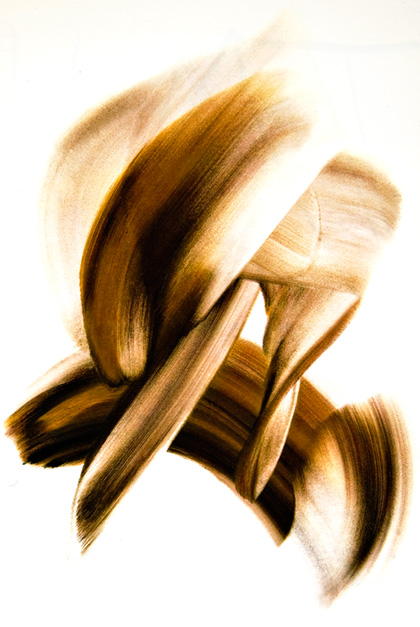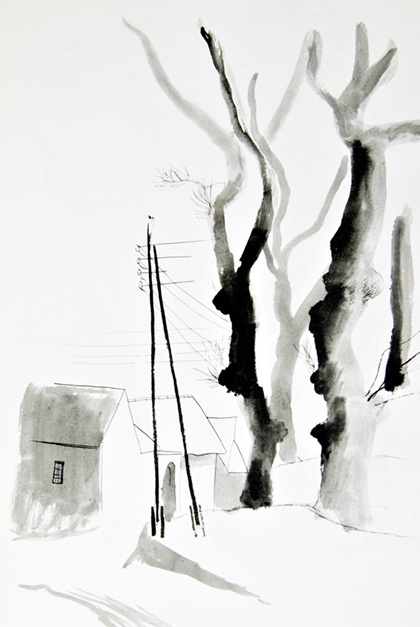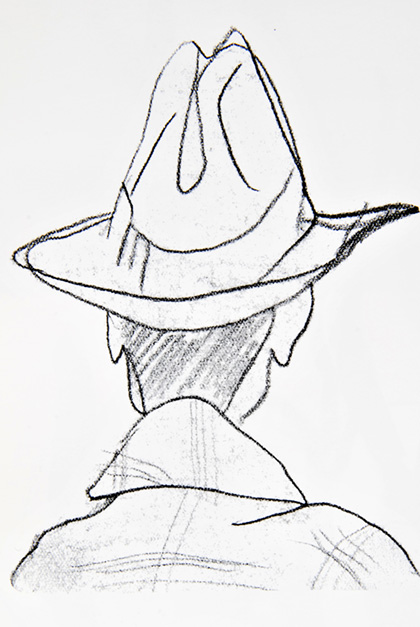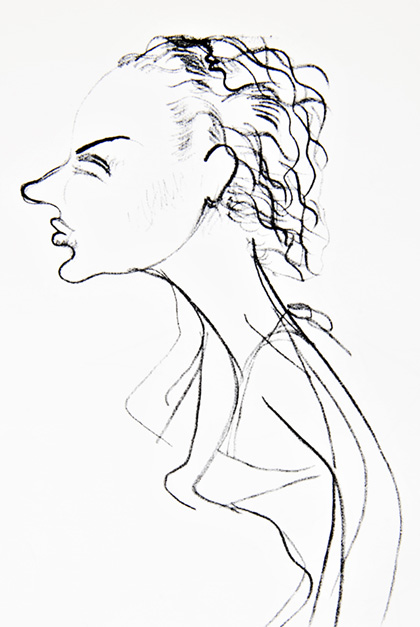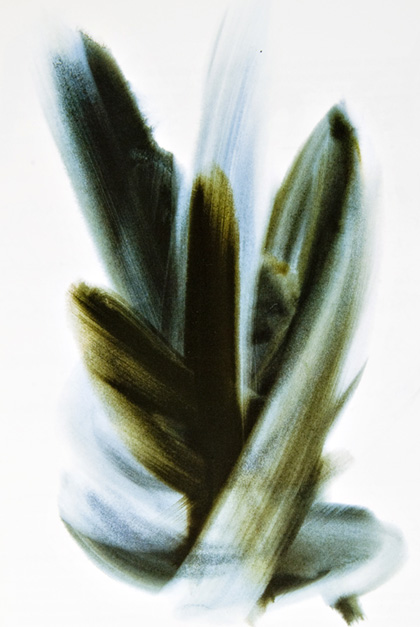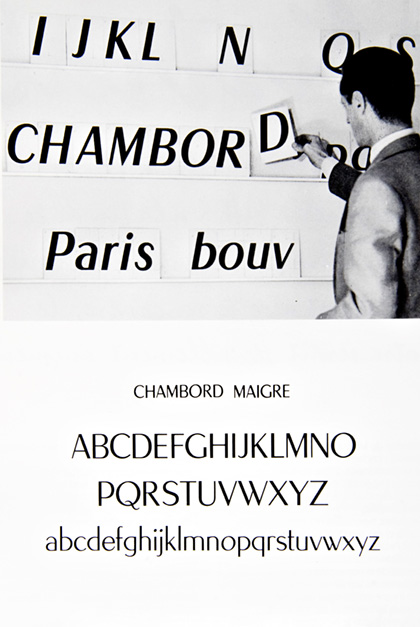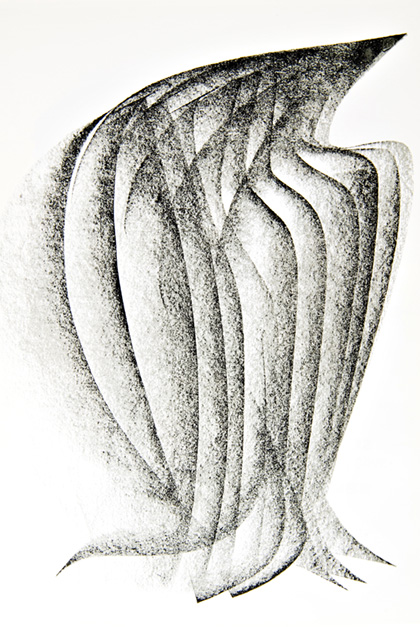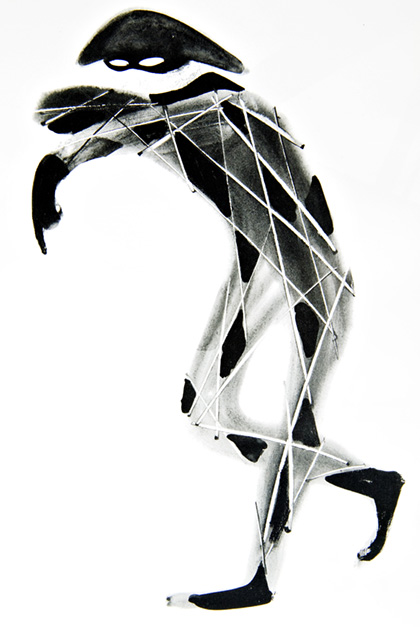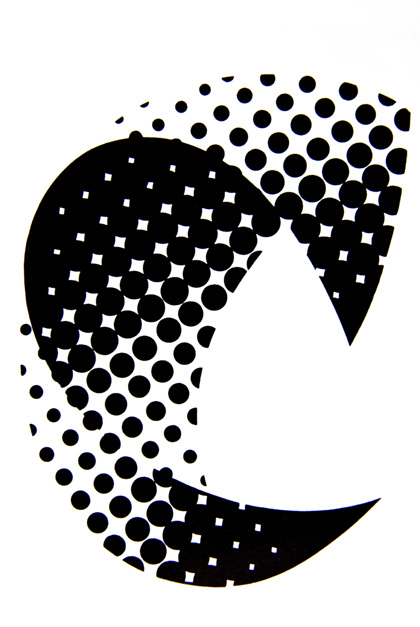
Roger Excoffon | Hommage au Graphiste et à l’homme | reloaded
À l’heure où j’entends que le nouveau logo d’Air France va parcourir la blogosphère à la vitesse du Concorde multiplié par 1000, je profite de republier ce billet sur Roger Excoffon qui fut le créateur inspiré du précédent logotype. Nous en reparlerons.
Ces images sont issues du catalogue de l’exposition qui se tint au Musée de la Monnaie peu après la disparition du maître. Ce catalogue est introuvable et il constitue une véritable somme, un résumé très complet de l’œuvre de Roger Excoffon. Vous pouvez en attendant les textes définitifs de cette chronique, consulter ce que j’ai déjà produit dans un billet précédent sur Roger Excoffon ici.
Le cas de Roger Excoffon est celui d’un des très grands artistes contemporains.
Artiste tout court: car le graphiste prestigieux ne vient qu’ensuite. Il est peintre. Il aime Sa Provence. Le graphisme fut pour lui une vocation tardive. En moins de quinze années, la conjonction de Roger Excoffon avec la Fonderie Olive a doté la France de ce qu’elle n’avait jamais connu depuis ‘la Belle Époque’ de Georges Auriol et de Georges Peignot, au début de ce siècle; un interpète de la lettre, entièrement, foncièrement, intensément français.
Exclusivement. Plus gallo encore que latin ce qui a rendu son succès international.
Car vivacité ne veut pas dire facilité: Roger Excoffon, l’homme de la griffe et du paraphe est aussi celui de la force contenue; de l’improvisation, soit, mais vingt fois répétée… Un saut périlleux au ralenti. Il n’ a pas de règles apprises, mais une discipline de soi au sens monastique, déchirant – j’allais dire, calviniste. Ce qui lui permet d’être tout entier dans son œuvre, ce mélange d’accueil et de refus qui se résout (pour le spectateur) en une joie d’autant plus délicieuse d’avoir été difficile.
Il n’a pas pas pris de thèmes, comme la plupart d’entre nous, dans les actualités successives, les vieilleries savoureuses, un excès d’érudition, ou un radar accrocheur de tous snobismes. Il est ‘entré en publicité’ comme on entre en loge: avec la volonté et aussi le pouvoir d’engager dans une action décisive et publique les fruits d’une jeune maturité.
Du premier jet, sans avoir passé par les filières, Excoffon s’est trouvé à l’échelon supérieur du métier publicitaire. Ce qu’il n’oserait pour lui, qui intimiderait sa toile — publicitairement il l’ose. Pour le client, il a l’audace de l’audace. Et le public, l’homme-de-la-rue, qui comprend vite et loin, est heureux avec lui.
Louons les dieux d’avoir tiré ce peintre-dessinateur (il y a peu) du culte du moi-seul, pour le jeter tout vif sur le papier agile, entre les rouleaux rapides, dilué dans l’encre odoriférente… le matériau de notre temps.
Maximilien Vox
‘Angoisse, top zéro’
‘Ce possible qui est ailleurs impossible: une œuvre d’art’
‘Extrait d’une lettre d’Excoffon à John Dreyfus, que celui-ci fit composer en Mistral pour l’édition 1956 du Penrose Annual. La composition anglaise ne tenait pas compte ici des accents français.’
‘Caractère Diane’
‘Première lettre d’un alphabet commandé par Berthold en 1970 et resté inédit.’ Il faut avoir été sur la table du dessinateur où s’empilent les innombrables calques, sur lesquels se polit indéfiniment, la courbe d’un a, d’un b, d’un c…etc. pour sentir ce qu’est cette ‘typographie’ du compte-fils, de même qu’il faut avoir pris en main la composition de plomb et l’avoir retournée pour comprendre ‘la typographie de l’envers’.
‘L’intelligence crée des relations nouvelles’.
‘On ne fait pas de bonne typographie sur un mauvais texte’.
‘Effigie de Marianne pour la déclaration de revenus de 1973, tiré à 80 millions d’exemplaires’.
‘Étude pour le renouvèlement de l’image de marque Air France (1968)’
‘Petit Larousse Illustré’
‘Grande Encyclopédie Larousse ‘l’infini des connaissances’.
‘Créé pour l’Exposition Française de Montréal en 1963, le graphisme du ‘coq’ a été réédité en affiches et affichettes destinées à l’annonce des Semaines Françaises en Suisse en 1965, 1966 et 1967 et pour l’Exposition Française de Tokyo en 1966 ainsi qu’en couvertures du Graphis Annual 1966, et de la revue éditée par la Chambre de Commerce Française des États Unis. Ajoutons que ce graphisme, en mouvement, illustra le générique en noir et blanc des actualités cinématographiques ‘Pathé-Magazine’.’
‘Affiche de prestige Air France (1965)’.
‘Sous le mécénat de la publicité le visuel peut éclater’.
‘Image de marque de la Caisse d’Épargne en couleur et en noir et blanc graphique’.
‘Les œufs NB’.
‘Avec ce timbre, qu’il nous offre aujourd’hui, c’est le même enchantement. Dédaignant les allégories faciles, il s’empare des deux vieilles initiales de la République Française, les arrache à leurs frontons où elles prenaient racine, les fait refleurir, les teinte de bleu, les noue et, du geste auguste du semeur d’étoiles, les projette dans l’immensité du ciel postal’. Savignac
‘Si vous savez écrire, vous savez dessiner’